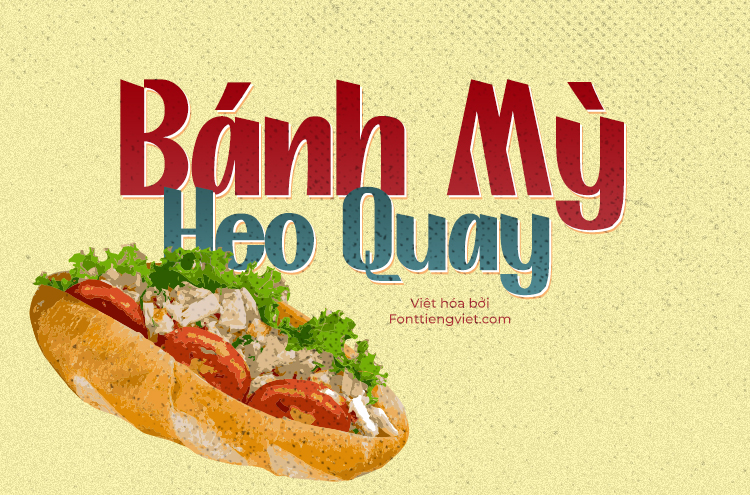
Font việt hóa 1FTV thiết kế ẩm thực 1
Trong lĩnh vực đồ họa, việc lựa chọn Font Miễn Phí phù hợp đóng vai trò then chốt giúp món ăn trở nên hấp dẫn hơn. Font việt hóa 1FTV thiết kế ẩm thực 1 là giải pháp hoàn hảo dành cho các bạn học sinh và nhà thiết kế đang tìm kiếm sự phá cách. Bộ font này không chỉ mang nét vẽ mềm mại mà còn giữ được sự chuyên nghiệp trong từng nét chữ Việt. Với sự kết hợp tinh tế giữa nghệ thuật và công nghệ, đây chính là công cụ giúp các dự án sáng tạo về thực phẩm đạt được hiệu quả thị giác tối đa.
Lợi ích khi dùng Font việt hóa 1FTV thiết kế ẩm thực 1
Bộ font được tối ưu hóa hoàn toàn cho bảng mã tiếng Việt, giúp người dùng không còn lo lắng về lỗi hiển thị dấu. Đây là ưu điểm lớn nhất khi thực hiện các bài thuyết trình hay thiết kế poster tại trường học.
Ứng dụng đa dạng trong trang trí
Bạn có thể sử dụng font chữ này để làm menu cho các quán trà sữa, bìa sách nấu ăn hoặc các nhãn dán sản phẩm thủ công. Đường nét của font gợi lên cảm giác ngon miệng và gần gũi với thực khách.
Độ tương thích cao với phần mềm
Kết luận về bộ font ẩm thực